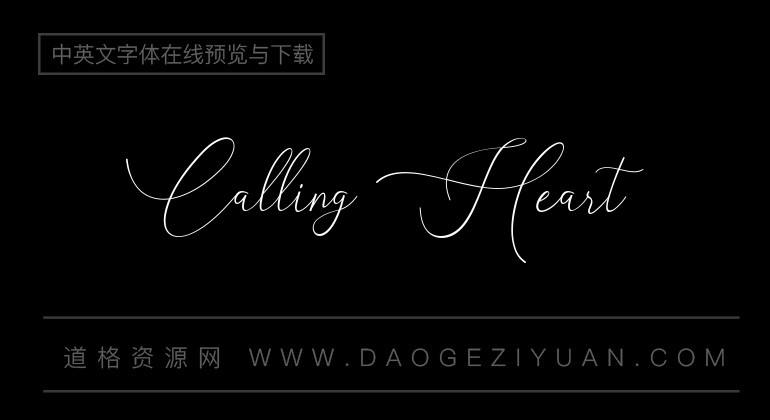
Calling Heart
Calling Heart 是一款手写体字体,由Gustavo Dipre创作。它具有温柔而优雅的风格,让人感到温馨,充满活力。字体具有圆润的笔画,每个字母都具有独特的设计,使其具有一种柔和的感觉。它也具有优质的可读性,可以用于各种文档,卡片,海报等。它的设计特点是它的灵活性,可以用于各种不同的主题和风格,使其具有多种用途。
Calling Heart是一款非常不错的手写艺术字体,具有很好的视觉感,适合于文化类的宣传设计、商业类品牌的广告和产品包装设计以及个性化文字排版等较多场景。
Calling Heart字符映射图